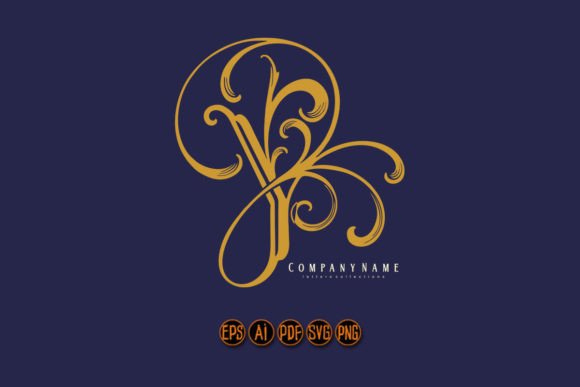
Modern Elegance Refreshed Gold Y Letter
Mencari elemen reka bentuk yang sesuai boleh menjadi mencabar, tetapi Modern Elegance Refreshed Gold Y Letter menawarkan koleksi luar biasa yang menaik taraf karya anda serta-merta.
Dicipta dengan ketepatan, Modern Elegance Refreshed Gold Y Letter menyediakan vektor yang bersih, tipografi yang licin dan lesen komersial untuk ketenangan fikiran.
Sama ada anda mencipta produk POD (Print on Demand), jemputan perkahwinan atau grafik media sosial, Modern Elegance Refreshed Gold Y Letter amat bersesuaian.